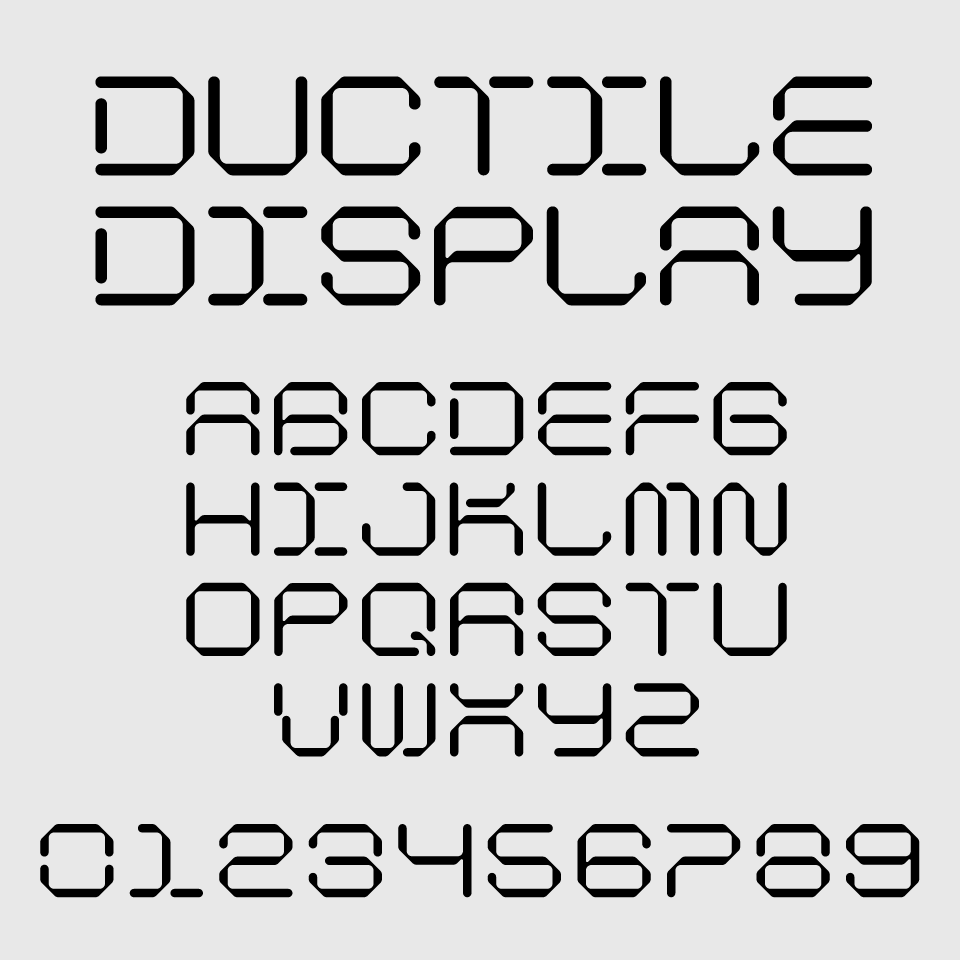
Ductile Display フォントは、工業的で未来感のあるデジタルルックが印象的なディスプレイフォントです。
文字はオクタゴン(八角形)をベースにした構造で、線が途切れたようなデザインが特徴。デジタル機器のディスプレイやサイバーパンク的な世界観を想起させるフォントです。
機械的でソリッドな印象を持ちながらも、角に丸みを持たせているため硬すぎず、洗練された印象も感じられます。テック系や近未来SFなどっぽい演出をしたいゲームUI、SFデザインとの親和性が高く、コンセプチュアルなビジュアルに強いインパクトを与えられるフォントです。